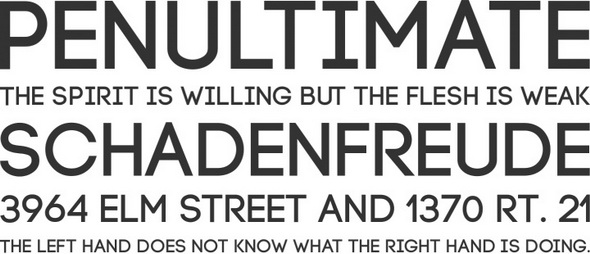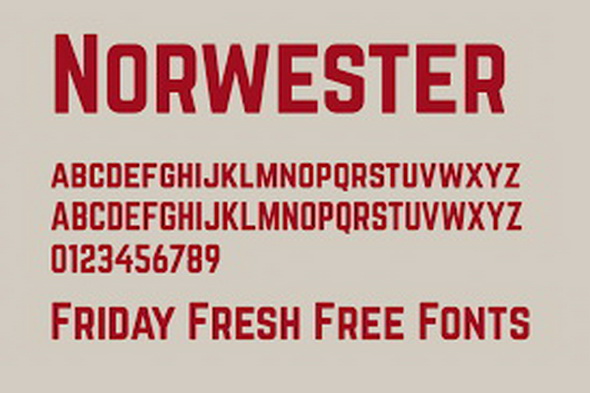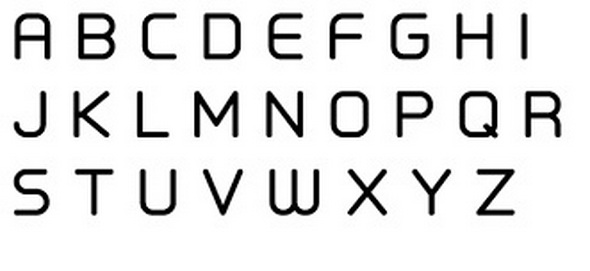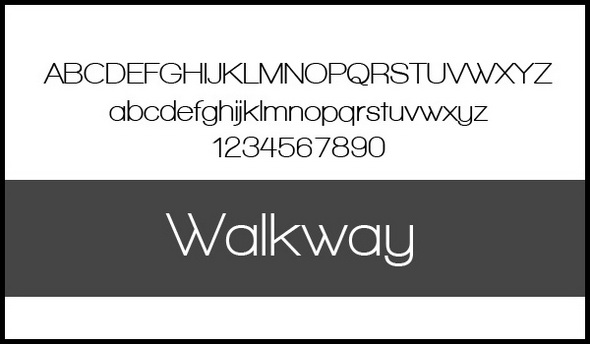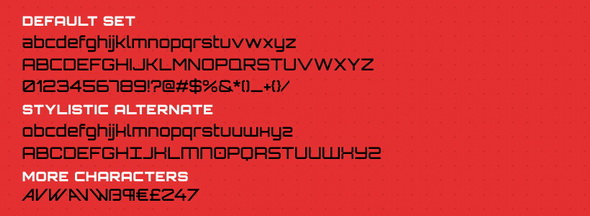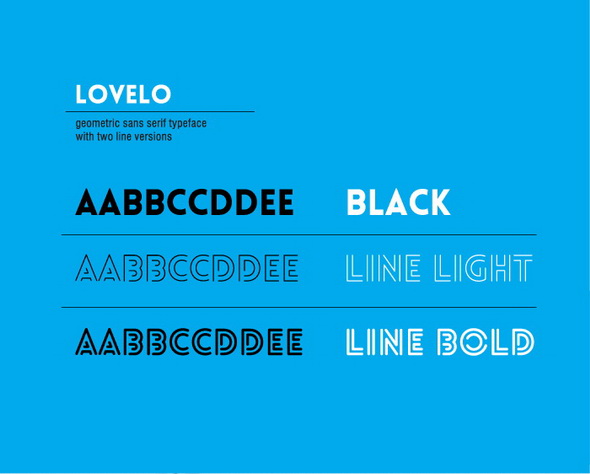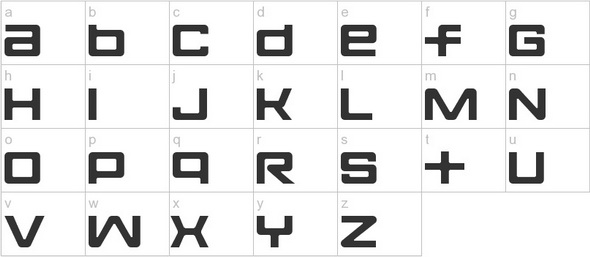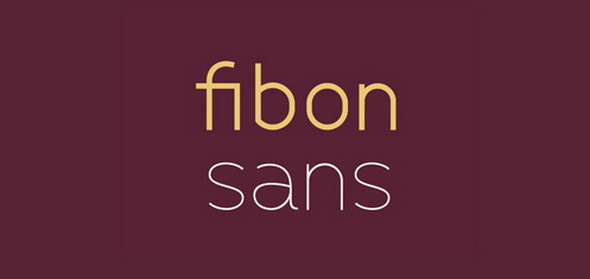
Геометрические шрифты для вашего дизайна
Геометрические шрифты — это шрифты, имеющие постоянную или почти постоянную толщину штрихов. Благодаря простоте написания и универсальности применения, очевидно, что это одна из самых распространенных разновидностей. Помня об этом, мы собрали подборку из 15 бесплатных шрифтов подобного типа, которые украсят коллекцию любого дизайнера.
Walkway
orbitron
lovelo
geometric shadow pw
fontopo solid
geometric black
fibon
geometric fog
geometric petras pw
code pro
galano grotesque
norwester
primus
dropy
rodriguez geometricpaper